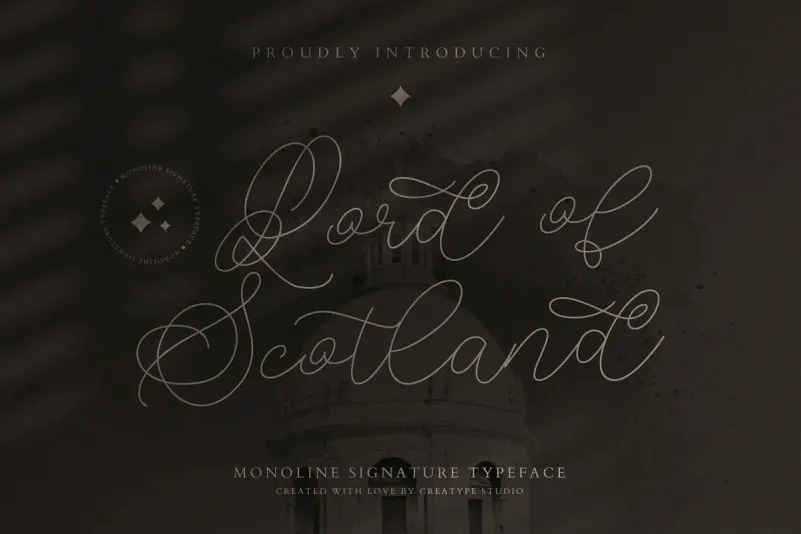
Lord of Scotland Font
A “Lord of Scotland Font” é uma elegante tipografia para script criada pelo Creatype Studio. Com seu estilo naturalmente autoral, ela carrega um ar refinado e sofisticado que certamente se encaixa perfeitamente num catálogo de fontes. Ideal para personalizar mensagens ou adicionar um toque único a qualquer projeto gráfico, esta fonte é uma escolha inteligente tanto para iniciantes quanto para profissionais. Se você busca incorporar o brilho e a elegância do handwriting moderno em seus projetos, essa é definitivamente uma fonte a considerar. Perfecta para adicionar um toque autêntico ao seu trabalho gráfico, especialmente quando criado no formato de script.